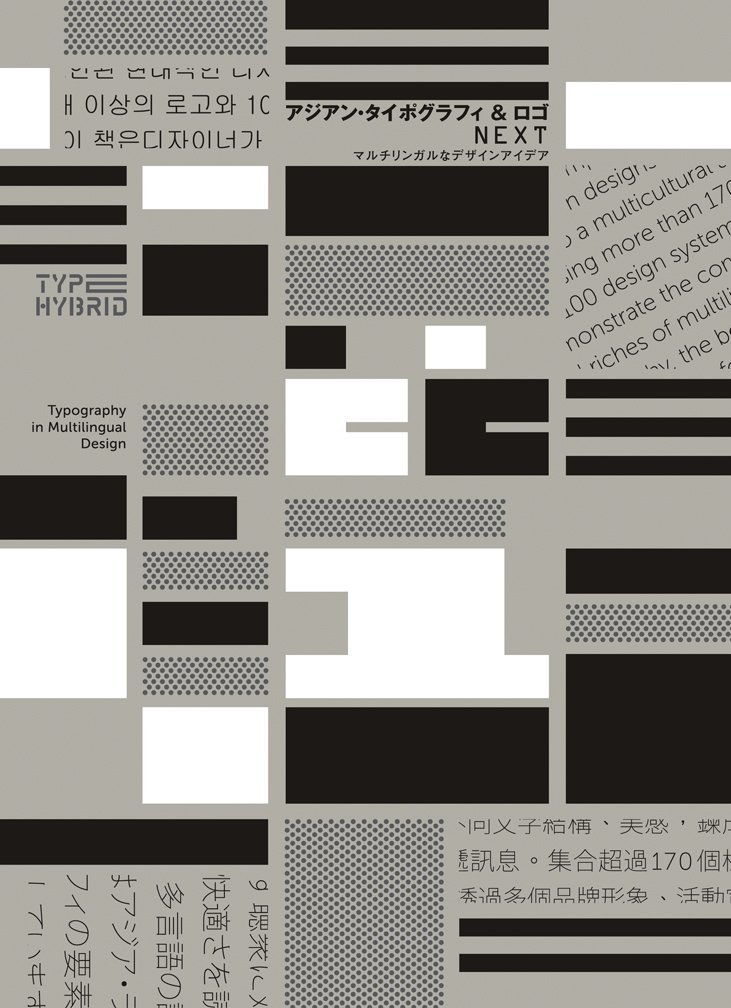
アジアン・タイポグラフィ&ロゴ NEXT マルチリンガルなデザインアイデア
ヴィクショナリー編集による、120種類以上のロゴや約100種類のイベントビジュアル、パッケージデザイン等を集め、解説した「アジアン・タイポグラフィ&ロゴ NEXT マルチリンガルなデザインアイデア」がグラフィック社から2016年7月7日に発売された。
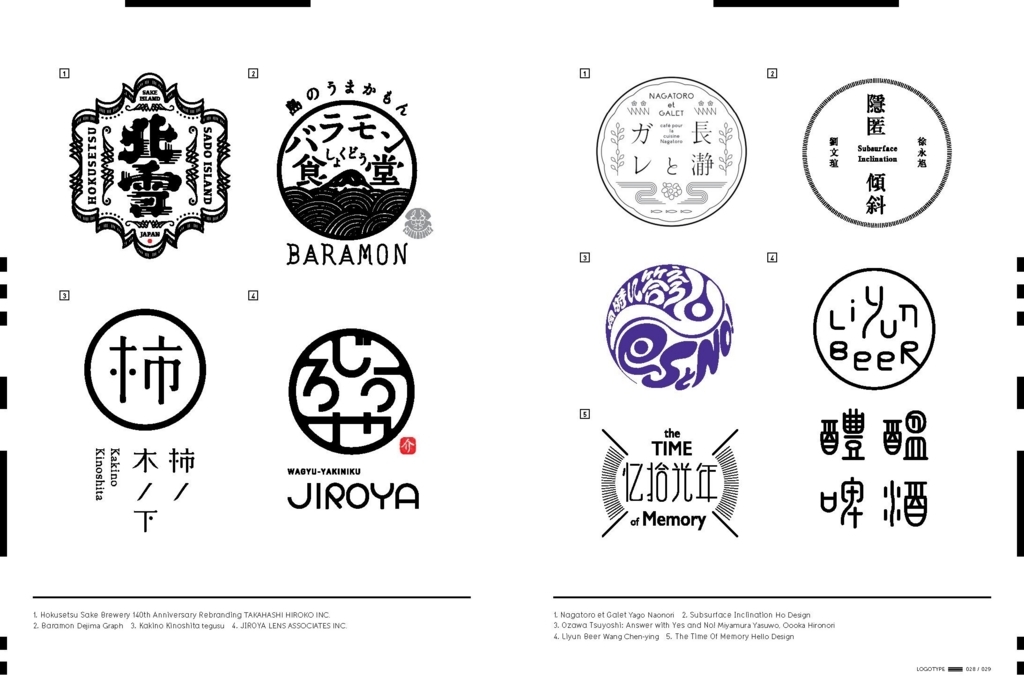
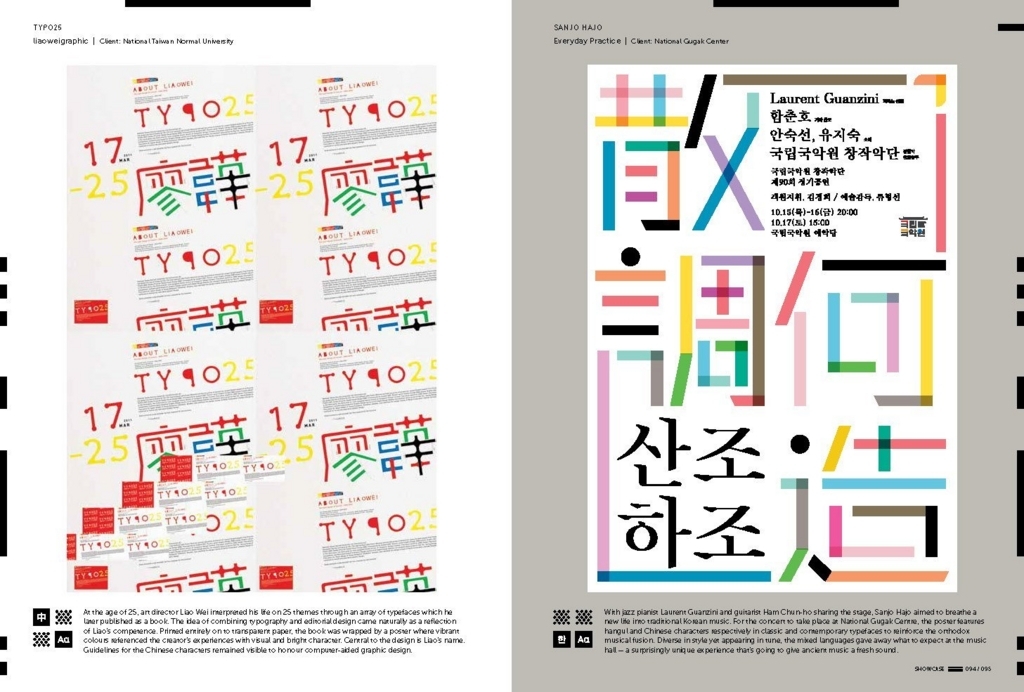
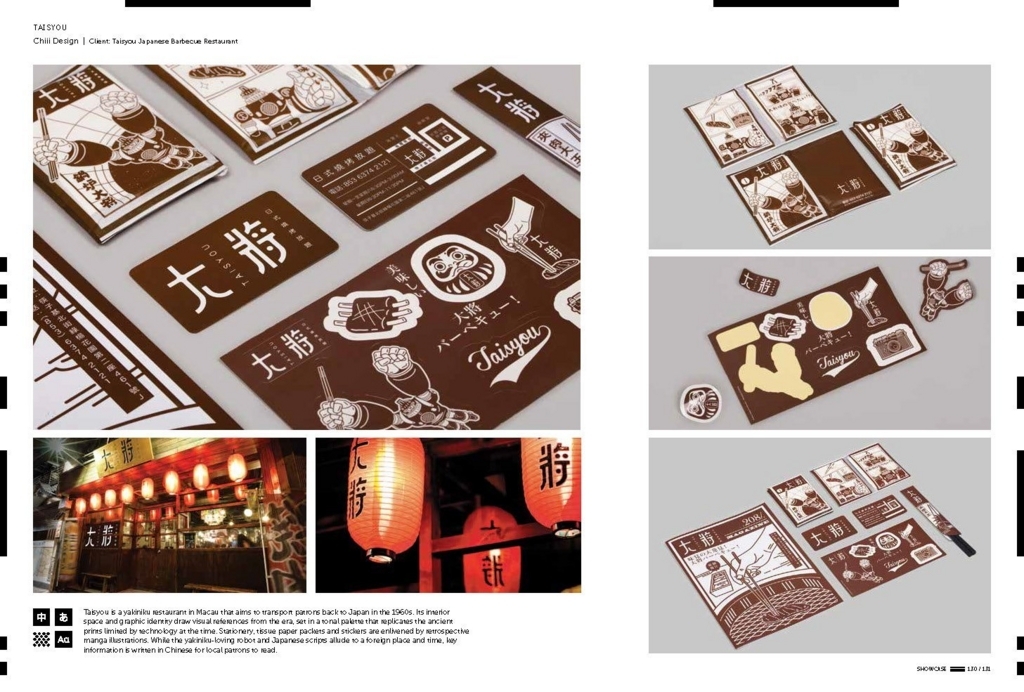
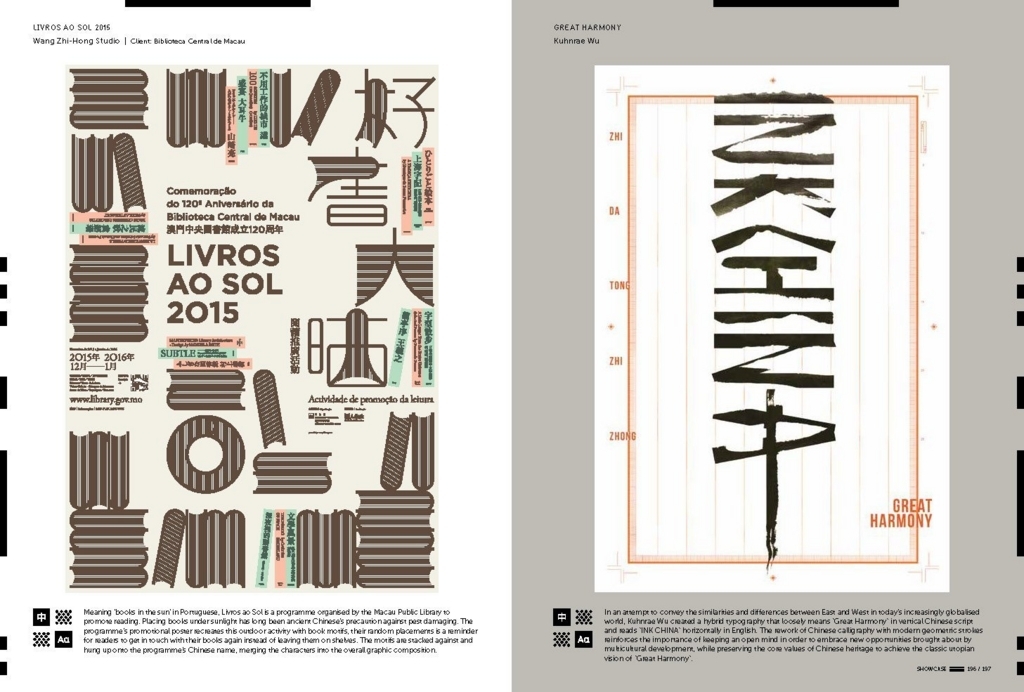
グローバル化によって、デザインに母国語以外の言語を採り入れることが多くなってきている今日この頃。『アジアン・タイポグラフィ & ロゴ NEXT』では、さまざまな言語が入り交じりながらもその組み合わせの妙を感じさせる120種類以上のロゴや約100種類のイベントビジュアル、パッケージデザイン等を集め、多言語のオーディエンスに訴えかけるための工夫を解説。それぞれの国特有の文字や文化的共通認識を調和させることで、異言語同士をどうデザインしていくのか。グローバル社会を生きる現代のデザイナー達の試みをとくとご覧下さい。